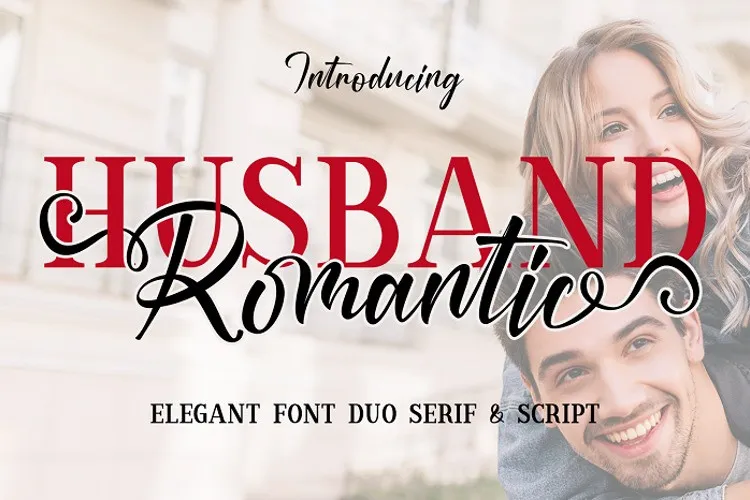
Aqui está uma breve descrição em português para a página de download da font ‘Husband Font Duo’, focada na categoria Script Fonts: ‘Husband Font Duo’ é uma fonte família que inclui duas estilos distintos: um estilo serif display e outro estilo calligrafia. Este conjunto de letras é perfeito para aplicativos como embalagens de produtos, projetos de marca, revistas, mídia social, e muito mais. Se você está procurando por inspiração criativa ou quer experimentar uma nova maneira de dar vida aos seus projetos, a adição desta fonte à sua coleção certamente o fará. Com seu charme elegante e versatilidade, esta família de letras se tornará um recurso essencial em qualquer projeto visual que você possa estar trabalhando. Não deixe de explorar as diferentes maneiras pela qual esta font pode adicionar uma nova dimensão à sua arte digital.